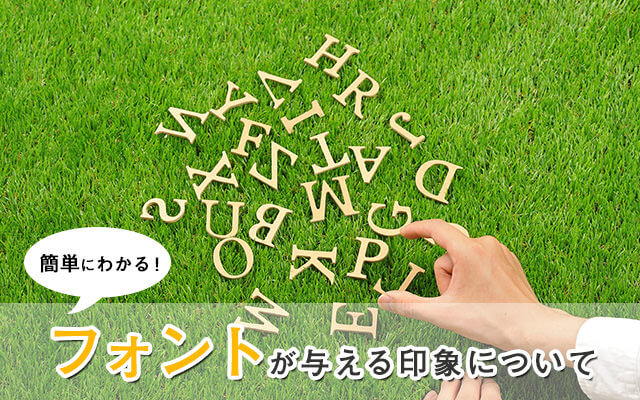
フォントが与える印象の違いとは?
さて、皆さんはホームページやポスターをデザインする際、どのフォントを使えばいいか迷ってしまうことはありませんか?
フォントは色と同様にホームページやポスターの印象を大きく左右する要素の一つとなります。
また、フォントの種類だけでなくその太さ細さによってそれぞれ印象は変わってくるためフォント選びは大変重要となってきます。
フォントを大きく二つにわけると「ゴシック体」と「明朝体」にわかれます。
欧文フォントでいうと「サンセリフ」と「セリフ」にわかれます。
今回はこの代表的な二つのフォントについてとそれぞれのフォントが与える印象についてお伝えしたいと思います。
ゴシック体とは?
全体的に動きが少なく縦横の線の太さがほぼ均一のフォントです。
ゴシック体は小さくなっても視認性に優れているためチラシや時刻表など幅広く使うことができます。
ゴシック体が与える印象
均等な太さで安定感のあるゴシック体は主に親近感、男らしさ、安定感、カジュアル、力強いという印象を与えますがそれらは太さによって読む人に与える印象が変わってきます。
太めのゴシック体は安定感があり、元気や力強いを感じさせますが、細くなると見た目が軽くなった分、洗練された女性的な印象になります。
明朝体とは?
縦線に比べ、横線が細くセリフ(三角形の山)がついているフォントです。
はねや払い、縦横の線に強弱があり動きがあるのが特徴です。
明朝体が与える印象
繊細さや優雅な印象を与える明朝体は筆使いを感じるフォントなので、和のテイストや伝統を感じるものに合います。
細いフォントであれば高級感や誠実さや上品さ、太いフォントであれば大人や固い印象を与えます。
ここでゴシック体と明朝体、それぞれのフォントを使用して作ったバナーで見比べていただきたいと思います。
ゴシック体
明朝体
親しみやすさや柔らかい印象を伝える際にゴシックを使用することで抵抗が少なくなり、逆に信頼性や堅実さなど、病院や法律事務所など信頼感を大切にしている企業には明朝体で表現するほうが優れています。
このようにフォントは同じ種類の文字でも大きさ、太さを変えるだけで見る人に違った印象を与えます。
お客様にどのような印象を与えたいか、企業のイメージにあったフォントはどれか見極めることが大切です。
印象や企業イメージからフォントを選び、どれが一番お客様に伝わるか是非フォント選びについて考えてみて下さい。